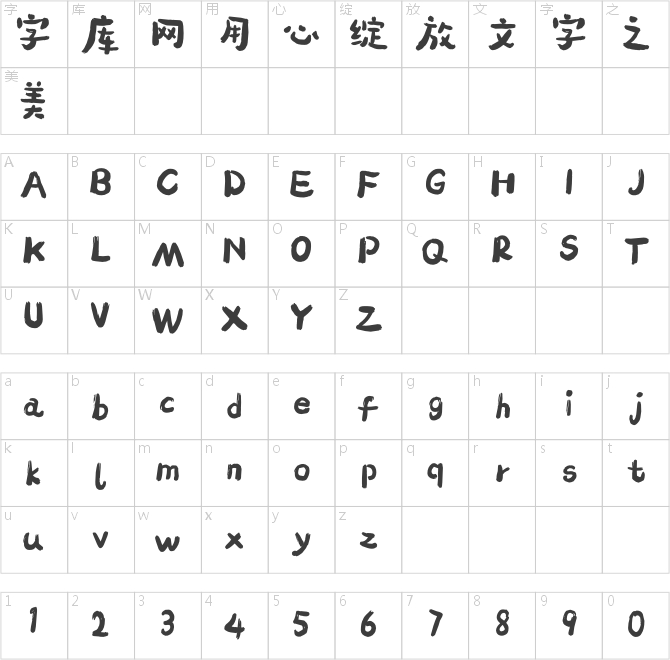
造字工房拙影體,其書風(fēng)活潑有趣,拙中見巧,字體結(jié)構(gòu)隨性自由、風(fēng)格俏皮可愛,具有很強(qiáng)的視覺感染力,此款字體適用于兒童讀物、報(bào)刊雜志標(biāo)題、廣告設(shè)計(jì)等視覺環(huán)境,有著極強(qiáng)的應(yīng)用空間。本字體為簡體字庫,采用OpenType/CID格式,Adobe-GB1-5編碼。基于中華人民共和國GB2312-80字符集標(biāo)準(zhǔn),另按需添加101個(gè)漢字。共收容字?jǐn)?shù)6864CJK漢字,ASCII常用字符100個(gè)。